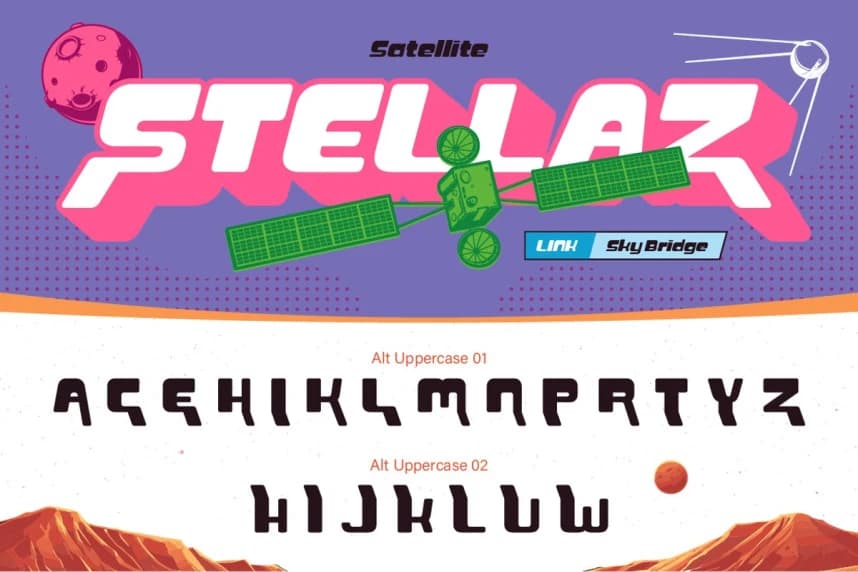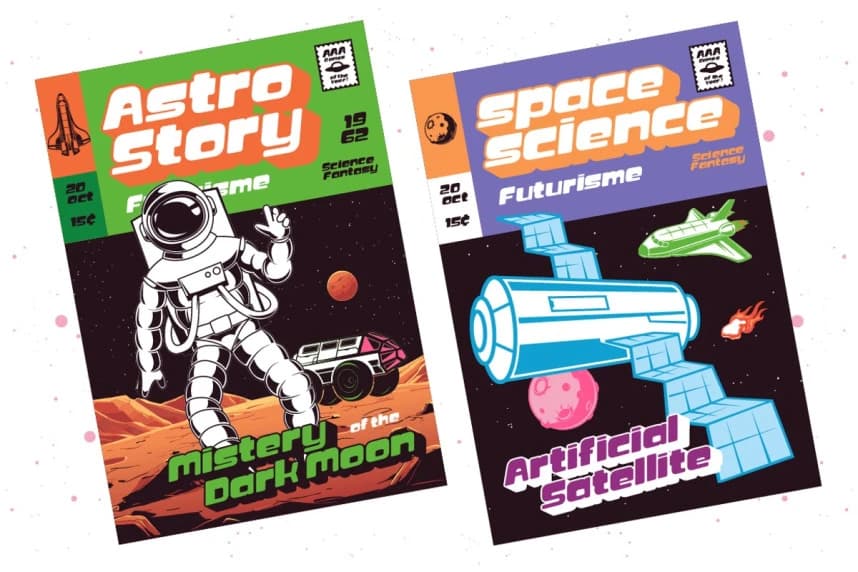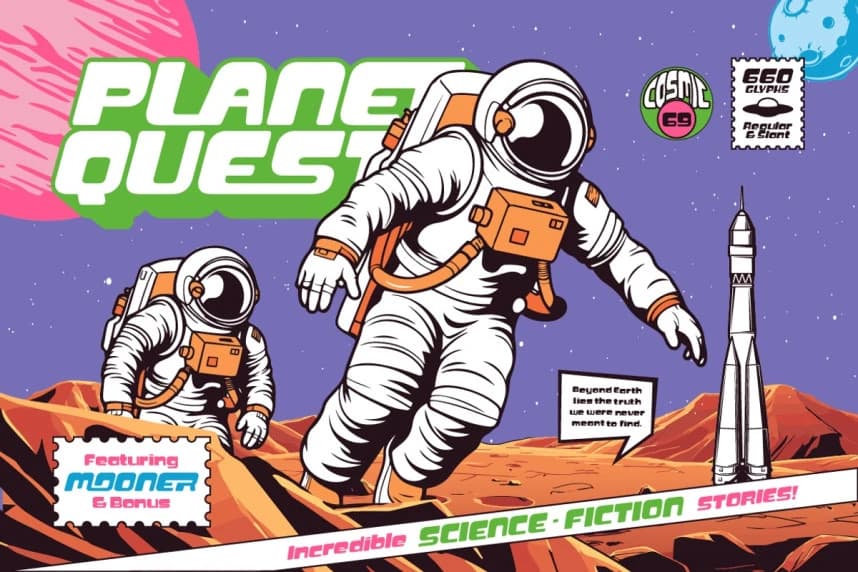
Zenfix Font
Zenfix Font, klasik bilimkurgu estetiğinden, uzay keşfinden ve vintage fütüristik tasarımdan ilham alan cesur bir retro-fütüristik gösterim yazı tipidir. Kalın hatları, yuvarlak köşeleri ve çarpıcı extrude stili ile Zenfix, nostalji ve modern enerjinin mükemmel bir karışımını yaratıcı projelerinize
Zenfix Font, klasik bilim kurgu estetiğinden, uzay keşfinden ve vintage futuristik tasarımdan ilham alan kalın bir retro-fütüristik gösterim yazı tipidir. Kalın hatları, yuvarlak köşeleri ve çarpıcı extrüde stiliyle Zenfix, yaratıcı projelerinize nostalji ile modern enerjinin kusursuz bir birleşimini sunar.